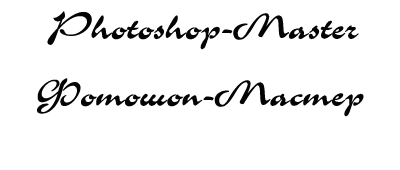
Обалденный шрифт! Очень полезно, спасибо!
Ахахах) Как плавленный сырок))) Спасибо)
Спасибо,часто использую этот шрифт)
Очень красивый шрифт
Мне нравиться. спасибо))
обожаю этот шрифт!!!
Хороший шрифт. Даже кажется, что я где-то видал надпись таким шрифтом...
КЛЁВО! спасибки
Красивый!
Клёвый!
прикольный.)
Мило же.
Ой какой прикольненький!
ой, хорошенький!